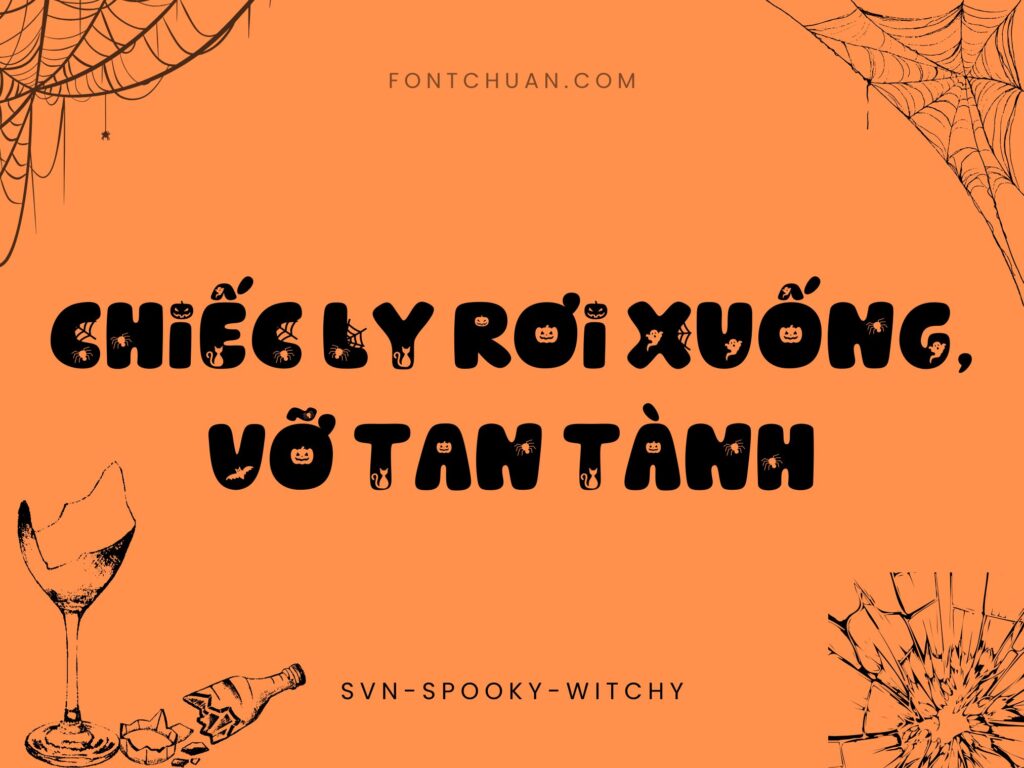
Font SVN Spooky Witchy là phiên bản Việt hóa của kiểu chữ Spooky Witchy, được thực hiện bởi STYLEno.1 Fonts. Đây là một Font Decorative hiển thị sans-serif độc đáo, được thiết kế bởi Jimtype Studio, mang phong cách huyền bí và ma mị, rất phù hợp cho các thiết kế liên quan đến Halloween hoặc các chủ đề kỳ bí. Font này nổi bật với các ký tự in hoa đồng nhất về chiều cao, kết hợp với các yếu tố trang trí đặc trưng như hình ảnh ma quái, tạo nên sự hấp dẫn và thu hút trong thiết kế. Spooky Witchy bao gồm đầy đủ các ký tự chữ hoa, chữ thường, chữ số và các ký tự đặc biệt, hỗ trợ đa ngôn ngữ, phù hợp cho nhiều mục đích sử dụng khác nhau như thiết kế poster, tiêu đề, logo và các ấn phẩm truyền thông.
SVN Spooky Witchy lý tưởng cho các dự án thiết kế yêu cầu sự huyền bí và ma mị, như thiết kế poster Halloween, tiêu đề, logo và các ấn phẩm truyền thông. Các ngành nghề như quảng cáo, giáo dục và công nghệ có thể tận dụng font này để tạo điểm nhấn trong thiết kế. Ngoài ra, font cũng thích hợp cho các sự kiện như Halloween, Tết, Giáng sinh và các lễ hội khác.